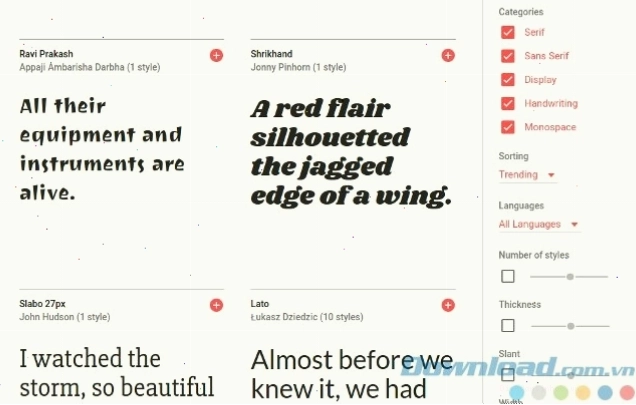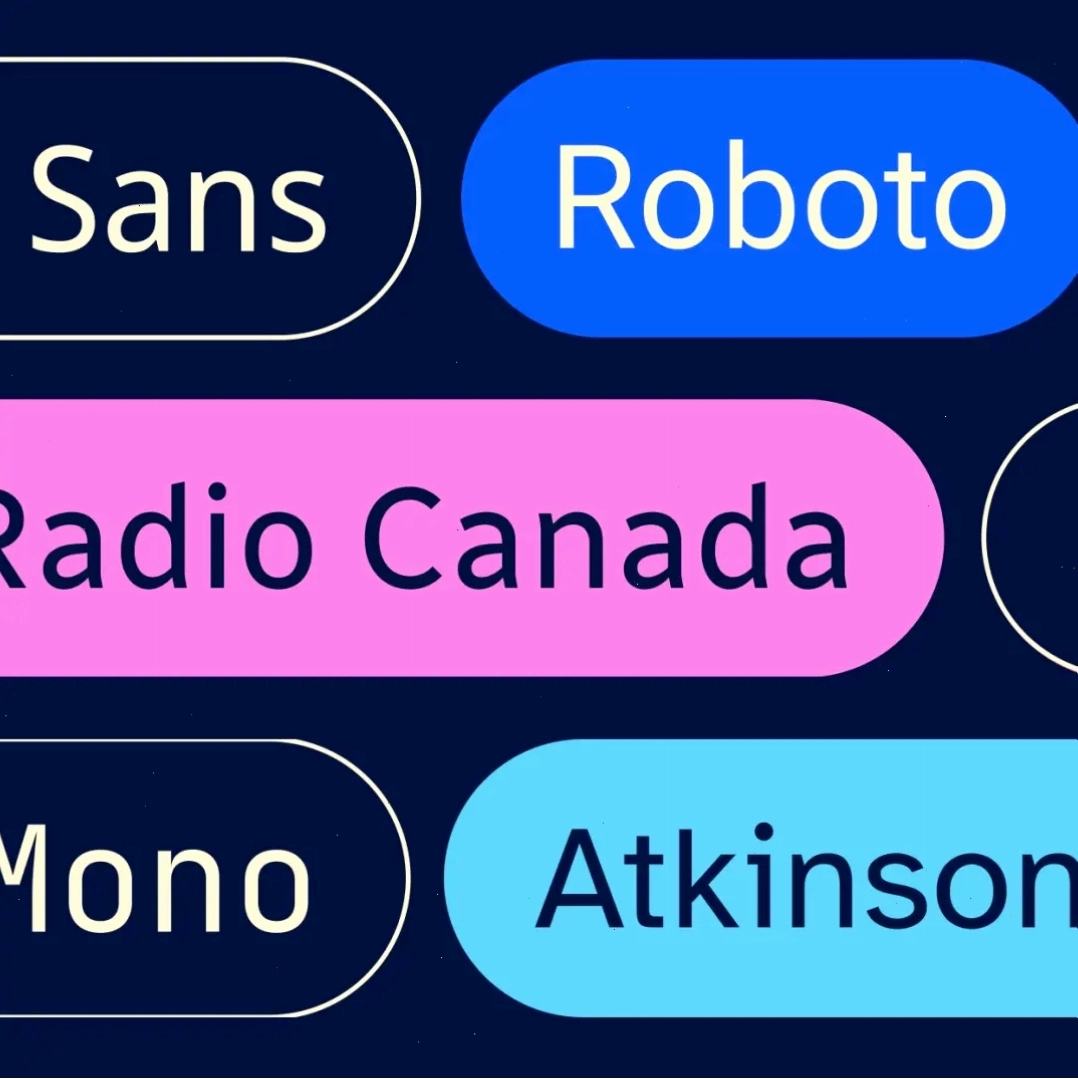
Khám phá Google Fonts: Tăng cường vẻ đẹp website với kho font chữ miễn phí
Trong kỷ nguyên số, một website không chỉ cần chức năng tốt mà còn phải sở hữu giao diện ấn tượng, thu hút người dùng ngay từ cái nhìn đầu tiên. Yếu tố thẩm mỹ này phụ thuộc rất nhiều vào việc lựa chọn kiểu chữ phù hợp. Google Fonts nổi lên như một giải pháp tối ưu, cung cấp một thư viện khổng lồ các font chữ miễn phí, đa dạng và chất lượng cao, sẵn sàng nâng tầm trải nghiệm thiết kế web của bạn.
Google Fonts là gì? Là một dự án của Google cung cấp hơn 1.300 font chữ mã nguồn mở, miễn phí sử dụng cho mọi dự án cá nhân và thương mại, hỗ trợ hơn 135 ngôn ngữ. Đây là công cụ đắc lực giúp nhà thiết kế web tạo ra những trang web đẹp mắt, chuyên nghiệp và độc đáo.
Tại sao nên sử dụng font Google cho website của bạn?
Việc tích hợp các bộ font chữ từ Google mang lại nhiều lợi ích thiết thực, đặc biệt là trong việc tối ưu hóa hiệu suất và trải nghiệm người dùng trên trang web.
Tăng cường tốc độ tải trang
Google Fonts sử dụng các kỹ thuật nén dữ liệu tiên tiến như WOFF 2.0. Điều này có nghĩa là máy chủ Google sẽ tự động gửi phiên bản file font có kích thước nhỏ nhất có thể tới trình duyệt của người dùng, dựa trên công nghệ mà trình duyệt đó hỗ trợ. Kết quả là trang web của bạn sẽ tải nhanh hơn đáng kể, đặc biệt quan trọng đối với những người dùng có kết nối mạng yếu hoặc không ổn định. Tốc độ tải trang nhanh không chỉ cải thiện trải nghiệm người dùng mà còn là một yếu tố quan trọng trong việc xếp hạng SEO của Google.
Kho font chữ đa dạng và cập nhật liên tục
Với hơn 1.300 bộ font chữ thuộc nhiều danh mục khác nhau, Google Fonts cho phép bạn dễ dàng tìm kiếm và lựa chọn kiểu chữ phù hợp với mọi phong cách thiết kế, từ trang trọng, chuyên nghiệp đến trẻ trung, sáng tạo. Các font chữ mới liên tục được bổ sung, đảm bảo bạn luôn có những lựa chọn thời thượng và độc đáo nhất.
Dễ dàng nhúng và sử dụng
Việc tích hợp font Google download vào website chưa bao giờ dễ dàng đến thế. Bạn có thể nhúng trực tiếp thông qua mã CSS hoặc tải về để sử dụng trên máy tính như các bộ font thông thường. Google cung cấp các công cụ hỗ trợ mạnh mẽ, giúp quy trình thiết kế giao diện trở nên đơn giản hóa.
Giao diện trực quan của Google Fonts hiển thị nhiều bộ font chữ đẹp mắt
Thư viện Google Fonts đa dạng, dễ dàng tìm kiếm và lựa chọn.
Tối ưu hóa cho trải nghiệm đa ngôn ngữ
Google Fonts hỗ trợ hơn 135 ngôn ngữ trên thế giới, bao gồm cả tiếng Việt. Điều này đảm bảo rằng các ký tự, dấu tiếng Việt sẽ hiển thị chính xác và đẹp mắt trên website của bạn, ngay cả khi sử dụng các font chữ không chuyên biệt cho tiếng Việt. Các font như font google đẹp, font google sans hay font google inter đều có khả năng hiển thị đa ngôn ngữ tốt.
Khám phá các loại font Google phổ biến
Thư viện Google Fonts vô cùng phong phú, nhưng có một số họ font chữ nổi bật nhờ tính ứng dụng cao và vẻ đẹp tinh tế, được nhiều nhà thiết kế ưa chuộng:
• Font Google Sans: Một họ font chữ tùy chỉnh được Google sử dụng trong các sản phẩm của mình, mang lại cảm giác hiện đại, rõ ràng và thân thiện.
• Font Google Inter: Được thiết kế đặc biệt cho màn hình, Inter là một lựa chọn tuyệt vời cho giao diện người dùng (UI) với khả năng đọc tốt ở nhiều kích cỡ.
• Font Google Pixel: Liên quan đến giao diện người dùng trên các thiết bị Pixel của Google, thường có thiết kế sạch sẽ và hiện đại.
• Các họ font Serif và Sans-serif đa dạng: Từ các font Serif cổ điển mang lại cảm giác trang trọng như Alegreya đến các font Sans-serif hiện đại, tối giản như Arimo, Asap.
Ví dụ về các kiểu chữ khác nhau của họ font Alegreya
Họ font Alegreya mang đến vẻ đẹp cổ điển và tinh tế.
Các biến thể của font Alegreya Sans với độ đậm nhạt khác nhau
Alegreya Sans với các biến thể linh hoạt cho nhiều mục đích sử dụng.
Mỗi họ font đều có những đặc điểm riêng biệt, phù hợp với từng loại nội dung và đối tượng mục tiêu. Ví dụ, các font google download mang phong cách serif thường phù hợp cho các bài viết dài, cần sự trang trọng, trong khi các font sans-serif lại được ưa chuộng cho tiêu đề, nút bấm và các yếu tố giao diện cần sự rõ ràng, hiện đại.
Tích hợp Google Fonts vào dự án thiết kế web
Quy trình tích hợp Google Fonts vào website khá đơn giản, bất kể bạn đang sử dụng nền tảng quản lý nội dung nào hay xây dựng website tùy chỉnh.
Các bước cơ bản để nhúng font chữ
1. Truy cập trang web Google Fonts (fonts.google.com).
2. Khám phá và lựa chọn font chữ mong muốn. Bạn có thể lọc theo danh mục, độ dày, độ nghiêng, v.v.
3. Nhấp vào nút 'Select this style' hoặc 'Add family' để thêm font vào danh sách lựa chọn của bạn.
4. Trong phần 'Selected families' (hoặc tương tự), bạn sẽ thấy các tùy chọn để nhúng font.
5. Nhúng qua thẻ <link>: Sao chép đoạn mã HTML được cung cấp và dán vào phần <head> của file HTML.
6. Nhúng qua @import: Sao chép đoạn mã CSS và dán vào file CSS của bạn.
7. Sử dụng font chữ trong CSS: Trong file CSS, định nghĩa các quy tắc sử dụng font chữ đã nhúng, ví dụ: font-family: 'Roboto', sans-serif;.